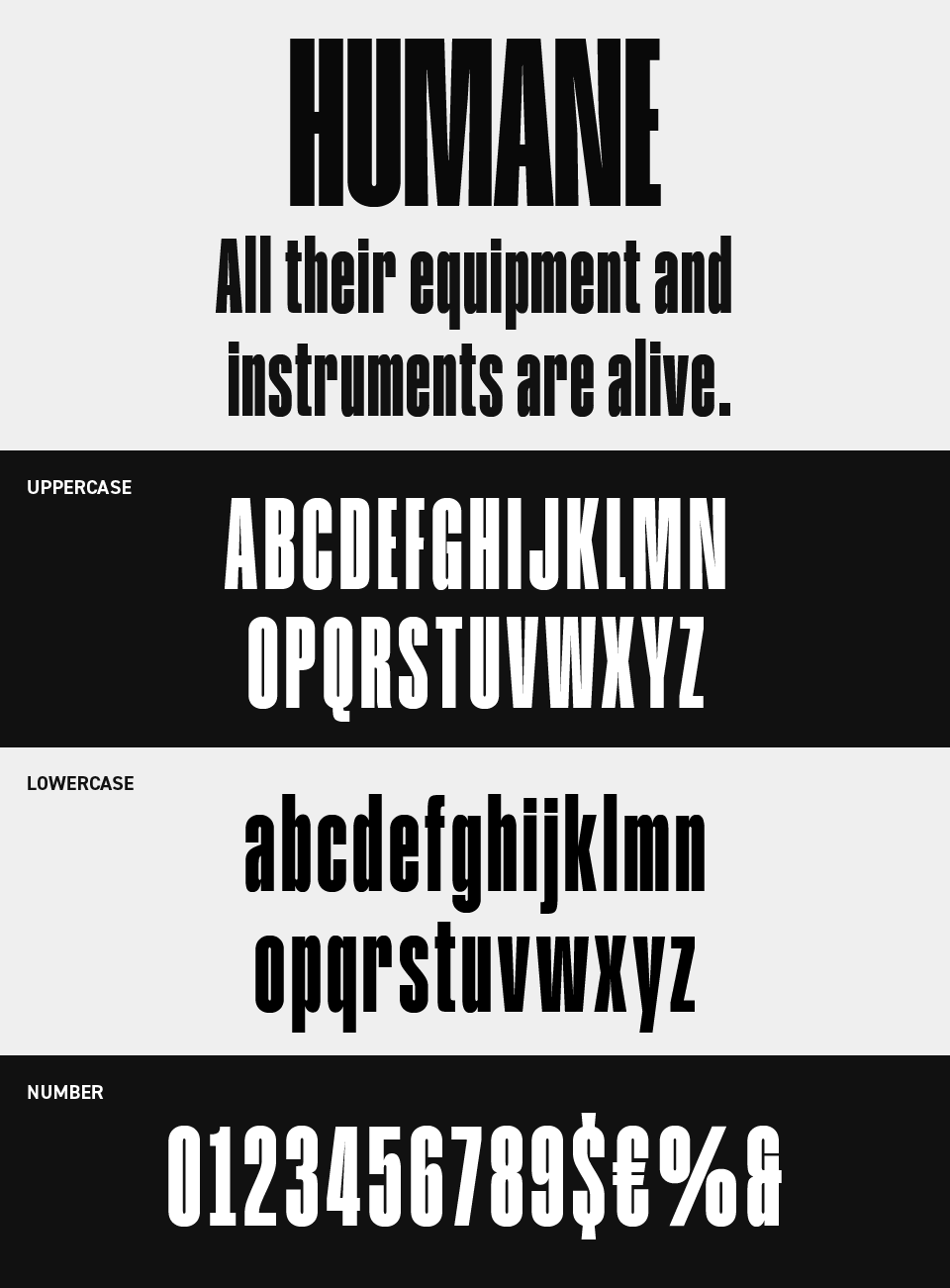
Humaneフォントは、ぐっと縦に伸びた極太のシルエットがインパクト大なサンセリフ体です。文字の隙間までギュッと詰まったデザインは、無骨だけどどこかリズミカル。
迫力のある佇まいながらも、レトロなポスターやジャズのレコードジャケットを思わせるような懐かしさも。パワフルでちょっと粋な印象を与えてくれるフォントです。